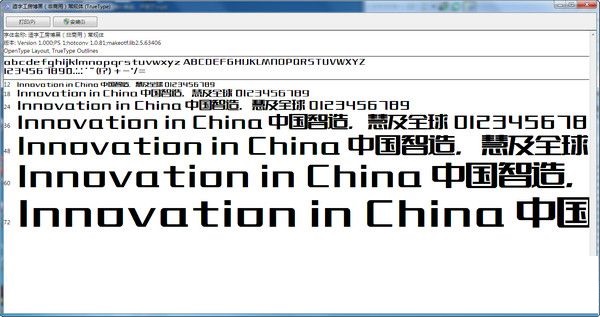
造字工房博黑字體是一款商業(yè)宣傳字體,字體端正、設(shè)計(jì)鮮明,非常適合設(shè)計(jì)方面的工作人員下載,歡迎使用!
此款字體看起來非常的端正、具有藝術(shù)感,很適用宣傳設(shè)計(jì)、創(chuàng)意設(shè)計(jì)、藝術(shù)設(shè)計(jì)等方面